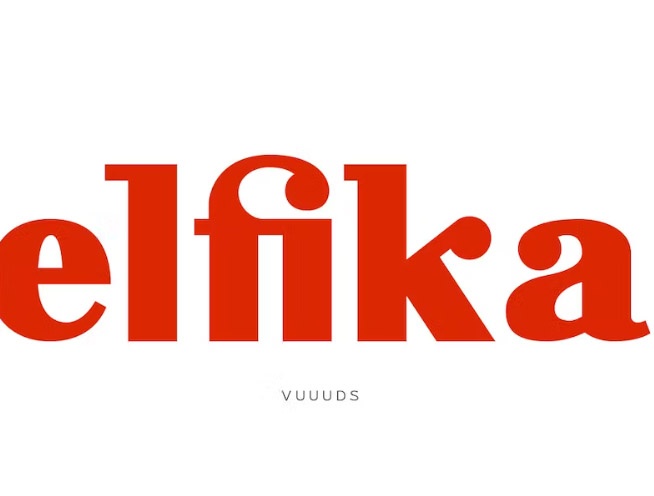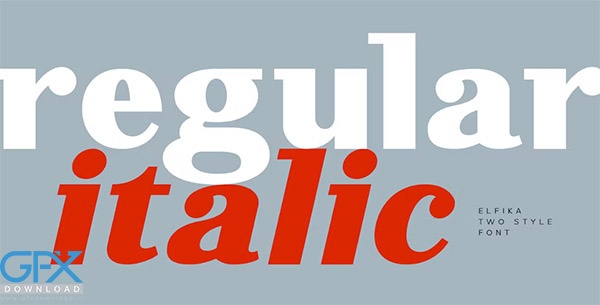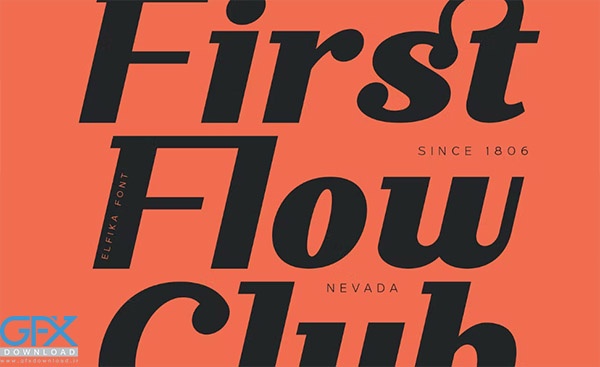
دانلود فونت انگلیسی ترند Elfika. یک فونت سریف مدرن است که با سبک معمولی و ایتالیک ارائه شده است. تک تک حروف با دقت ساخته شده اند. این فونت شامل علامت متنی زیبا است. فونت انگلیسی ترند Elfika شما می توانید از طریق Font Book (کاربر مک) یا نقشه کاراکتر ویندوز (کاربر ویندوز) به علامت جایگزین دسترسی داشته باشید.
شما می توانید در طراحی های مختلف از این فونت انگلیسی زیبا استفاده نمایید و برای برندسازی، پروژه های شخصی و غیره مناسب است.